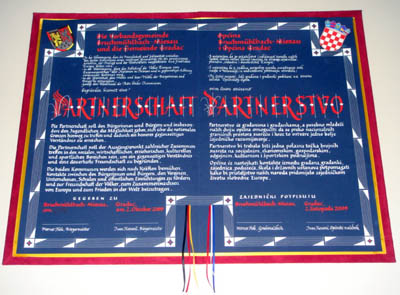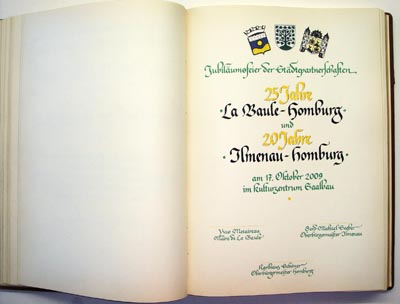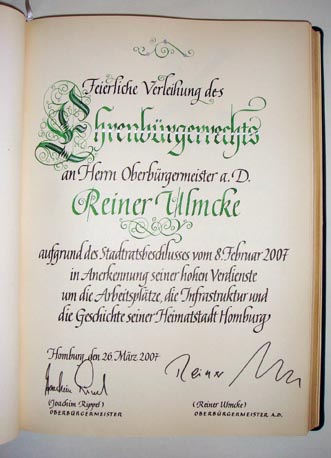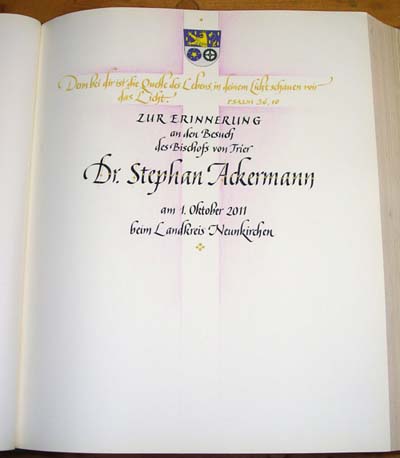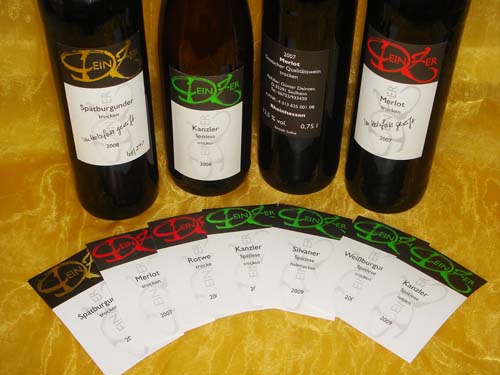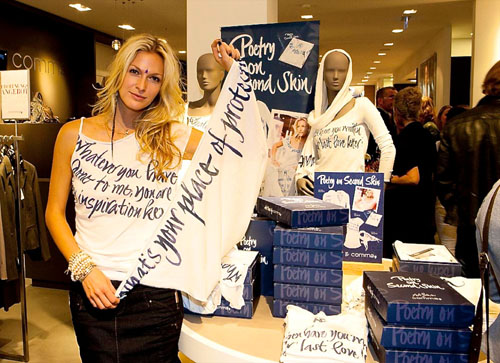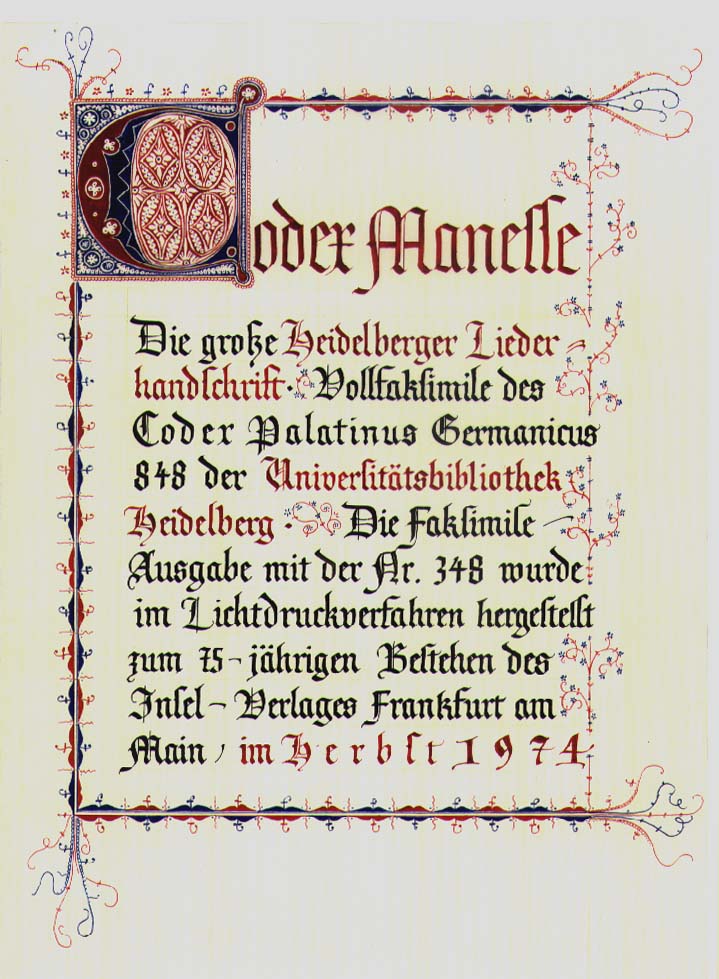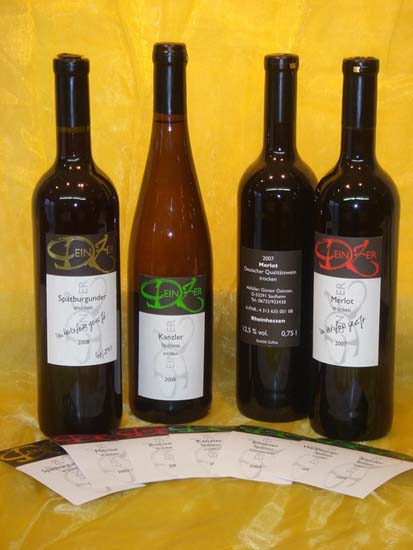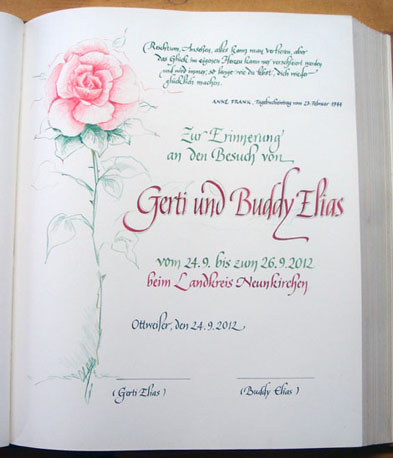
Schriftgrafiken nach historischen Vorbildern
(Urkunden, Diplome, Grundsteinlegung,
Städtepartnerschaft, Gästebuch, Goldenes Buch, Eid des Hippokrates
etc.)
Eid des Hippokrates: Beispiele
KOMMUNIKATIONSDESIGN & KALLIGRAFIE
Professionelle Schriftgrafik und Schriftanwendung in jeglicher Form.
Eintragungen
und Gestaltung von Urkunden, Goldenen Büchern,
Partnerschafts- oder Grundsteinlegungsurkunden, Diplomen, Stammbäumen.
Eid des Hippokrates. Menükarten, Einladungen, Glückwünsche zur Hochzeit,
zum Geburtstag oder Jubiläum, Briefumschläge, Liebesbriefe,
Dokumente in allen historischen Schriften. Grabsteinentwürfe.
Handschrift
jeglicher Art (von historisch bis modern, von klassisch bis expressiv)
Deutsche Schrift, Fraktur, Bastarda, Textur. Schriften vor Gutenberg.
Kommunikationsberatung und Verkaufsförderung
Gestaltung von Schriftzügen und Emblemen (Logo, Signet, Symbol, Wortmarke).
Kalligrafie, Typografie, Schriftgrafik für Öffentlichkeitsarbeit,
Events, TV und Film, Werbung,
Präsentationen, Gestaltung von Buchcovern, CD-Titeln, Plakaten etc. mittels
individuell gestalteter, handgeschriebener oder gezeichneter Schrift.
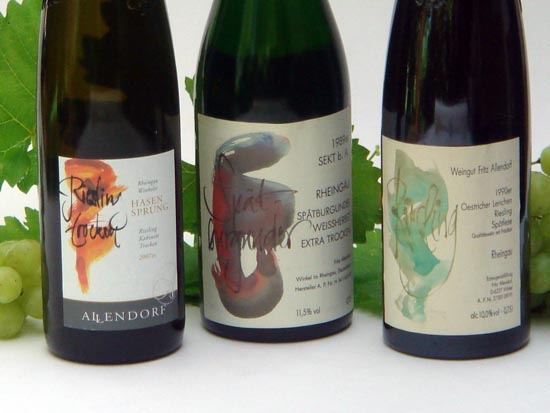
Weinetiketten für ein Weingut im Rheingau/Deutschland
Weinetiketten-Serie (Front- und Rückenetiketten) für ein Weingut in Rheinhessen/Deutschland
Original-Kalligrafie und Schriftgrafik
Gestaltung
von Original-Schriftgrafiken, Kalligrafien oder
handgeschriebenen Unikat-Büchern auf Anfrage.